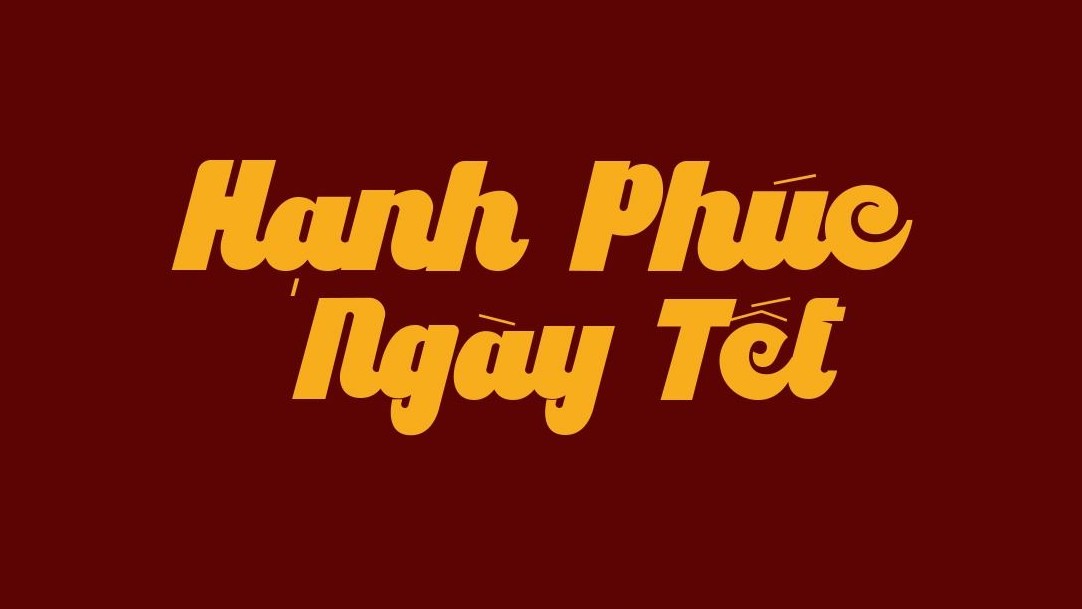
Font chữ tết là gì và ảnh hưởng đến cảm quan bao bì xuân?
Font chữ tết là hệ thống các phông chữ được thiết kế mang đậm phong cách văn hóa Á Đông, thường mô phỏng các nét bút lông thư pháp hoặc các đường nét cách điệu rạng rỡ. Đặc trưng của dòng phông này là sự uyển chuyển, bay bổng, gợi nhắc đến không khí hân hoan và lời chúc hanh thông dịp đầu năm.
Hiện nay, xu hướng thiết kế thường kết hợp giữa nét chữ truyền thống và cấu trúc hình học mới mẻ. Tuy nhiên, các bộ phông gốc thường không hỗ trợ đầy đủ bảng mã tiếng Việt, dẫn đến lỗi hiển thị các ký tự đặc thù. Bộ font chữ tết việt hóa tại In Viva đã được các kỹ thuật viên hiệu chỉnh Kerning và dấu thanh tỉ mỉ, giúp bản thiết kế luôn cân đối. Việc ứng dụng các phông chữ chuẩn giúp các ấn phẩm thương hiệu toát lên sự chỉn chu, chuyên nghiệp và bắt kịp xu hướng thẩm mỹ đương đại.
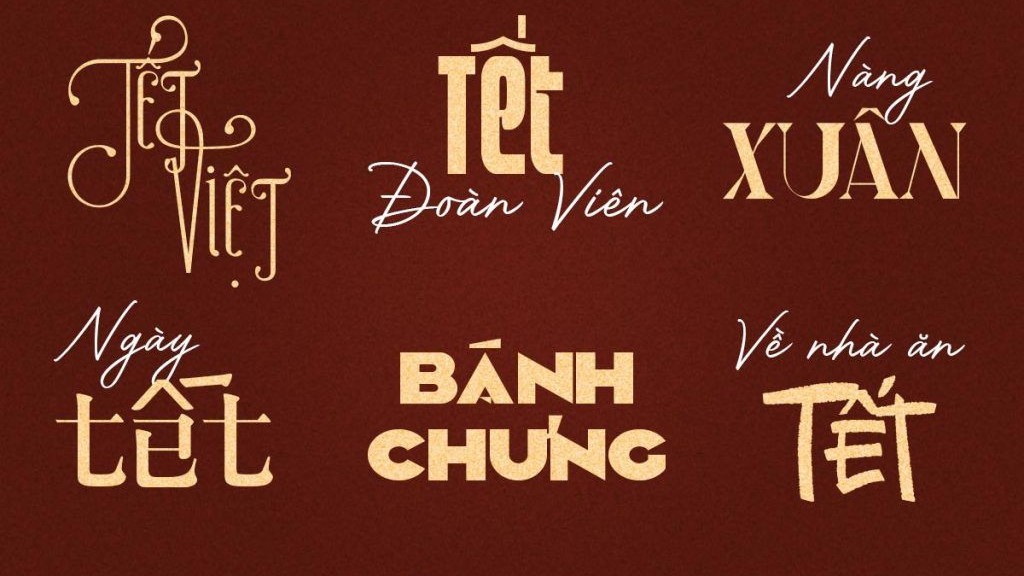
Lưu ý chuyên môn: Khi sử dụng font chữ tết đẹp cho mục đích in ấn hộp giấy cứng, kỹ thuật viên nên kiểm tra mật độ các nét xước trong tà chữ. Việc duy trì sự rõ nét giữa các khoảng hở giúp thành phẩm không bị hiện tượng mực loang làm mờ nội dung thông tin.
05 Công dụng của bộ font chữ tết trong thiết kế và sản xuất ấn phẩm
Sức hút của những đường nét nghệ thuật mang lại chiều sâu và giá trị riêng biệt cho các sản phẩm của doanh nghiệp trong mùa cao điểm:
- Sản xuất bao lì xì độc quyền: Phông chữ xuân là linh hồn của các mẫu lì xì. File chuẩn giúp các câu chúc như “Vạn sự như ý” hay “An khang thịnh vượng” hiển thị sắc sảo, tạo ấn tượng về một đơn vị uy tín và trân trọng khách hàng ngay từ cái nhìn đầu tiên.
- Thiết kế bao bì hộp giấy đặc sản: Font chữ này là lựa chọn phù hợp cho các dòng túi giấy đựng trà, bánh mứt hoặc thực phẩm khô. Hình ảnh chữ tết in trên bề mặt giấy cán màng mờ tạo cảm giác về sản phẩm sạch, chất lượng và mang đậm dấu ấn dân tộc.
- Thi công phông nền sự kiện tất niên: Sử dụng font chữ tết miễn phí chất lượng cao giúp các mẫu backdrop khổ lớn không bị răng cưa khi phóng to. Hình ảnh rực rỡ giúp không gian buổi lễ trở nên trang trọng và ấm cúng.
- Khắc laser tinh xảo trên vật liệu gỗ và tre: Các nét chữ tết khi được khắc trên bề mặt hộp gỗ hay bìa sổ tay tạo nên độ sâu tinh tế. Đây là giải pháp hiệu quả cho các dòng vật phẩm văn phòng mang phong cách truyền thống và thanh lịch.
- In nung gốm sứ và thủy tinh: Hình ảnh chữ nghệ thuật in nung dùng phông tết trên sứ trắng Bát Tràng là ấn phẩm đối ngoại nhã nhặn, có độ bền màu cao và không bị bong tróc dưới tác động của nhiệt độ.
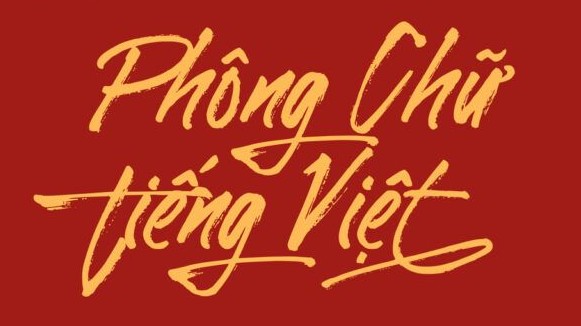
04 Lưu ý kỹ thuật khi sử dụng font chữ tết việt hóa trong sản xuất
Để thành phẩm sau in đạt độ mịn màng và trung thực với bản thiết kế rực rỡ, đội ngũ sản xuất cần chú trọng các vấn đề kỹ thuật sau:
- Kiểm soát độ dày nét chữ uốn lượn: Chữ thư pháp thường có những đường nét giao thoa phức tạp. Designer nên chủ động kiểm tra độ dày nét trong file gốc, đặc biệt khi thực hiện in lụa trên túi vải hoặc in Offset khổ nhỏ, để đảm bảo các chi tiết này không bị bết mực vào nhau gây mất thẩm mỹ.
- Tối ưu đường Path cho gia công bế nổi: Đây là khâu cực kỳ quan trọng khi thực hiện dập nổi (embossing) tiêu đề trên nắp hộp giấy cao cấp. Kỹ thuật viên cần xử lý mượt các điểm neo trong file vector để khuôn bế không bị sắc cạnh đột ngột, tránh hiện tượng nhăn mép giấy hoặc rách sớ giấy mỹ thuật của bao bì thành phẩm.
- Hiệu chỉnh hệ màu CMYK cho tông đỏ và vàng: Sắc đỏ rực rỡ của ngày Tết trên màn hình (RGB) thường sáng hơn khi in thực tế. Kỹ thuật viên tại xưởng cần thực hiện hiệu chỉnh thông số màu sắc và in lót một lớp mực trắng phù hợp để đảm bảo sắc thái của phông chữ luôn tươi tắn và chân thực dưới ánh sáng mặt trời hoặc đèn showroom.